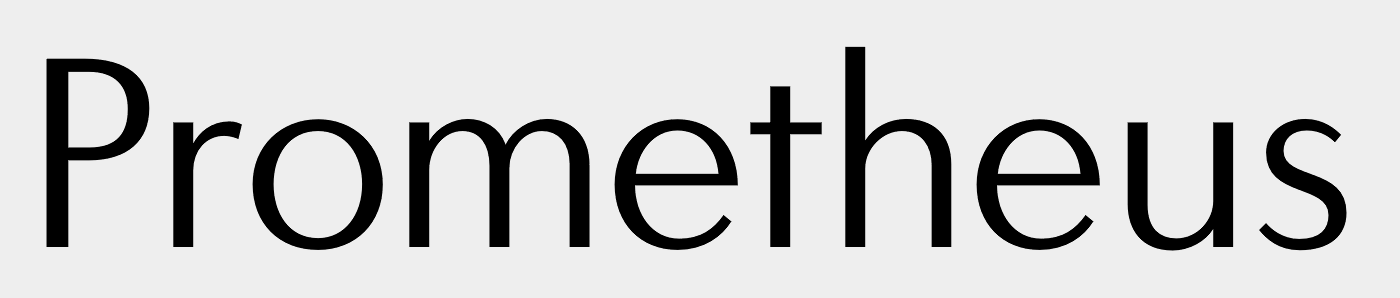
Humanistische Antiqua Sans whatever …
Ich bin auf der Suche nach der folgenden Type am Bild.
Falls jemand ausserdem noch Schriften weiß, die in diese Richtung bzw. auch zu Sang Bleu Sans, Beausite, Optima, etc. tendieren, wäre das ebenfalls toll!
diese beiden sind Dir vermutlich zu weit weg, gehen eher Richtung Optima, aber ich mag sie ganz gerne mit ihrem moderaten Strichstärkenwechsel und vielleicht bringen sie Dich und die Mitleser ja auf weitere Ideen. :-D
Dank auch  Kathrin und Norbert! Sehr hübsch, vor allem die Carisma. Ich würde etwas suchen, das mehr zu Sang Bleu tendiert.